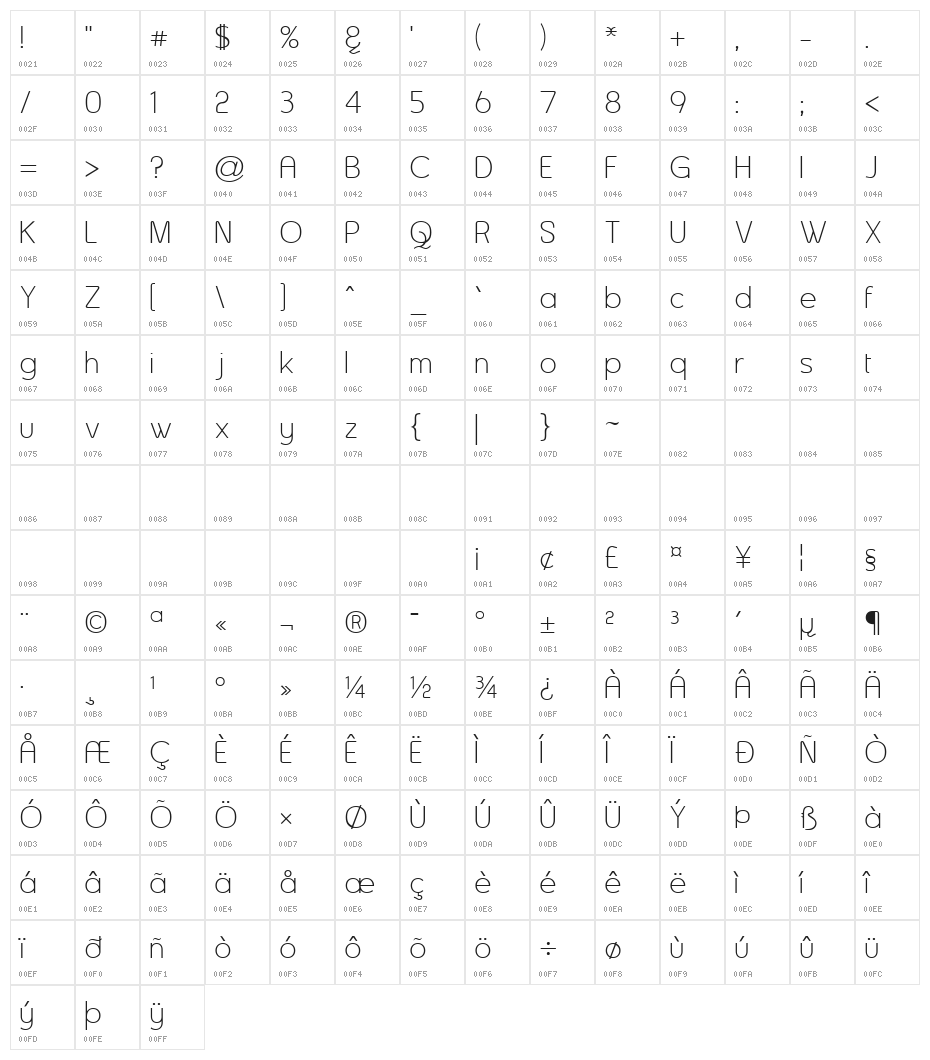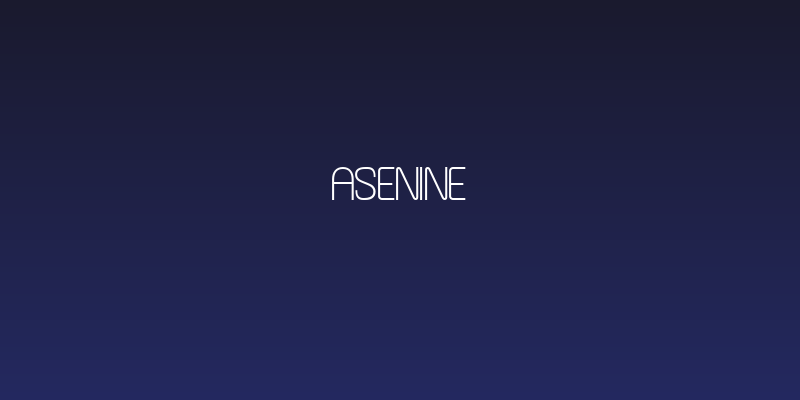
Asenine Font
| Categorías | Sans Serif |
| Caso de uso | Headlines, Body text, Logos |
| Proyectos propuestos | Ideal for branding, advertising, web design, and editorial layouts where a modern and clean look is desired. |
| Autor | Fonts by Apostrophic Lab |